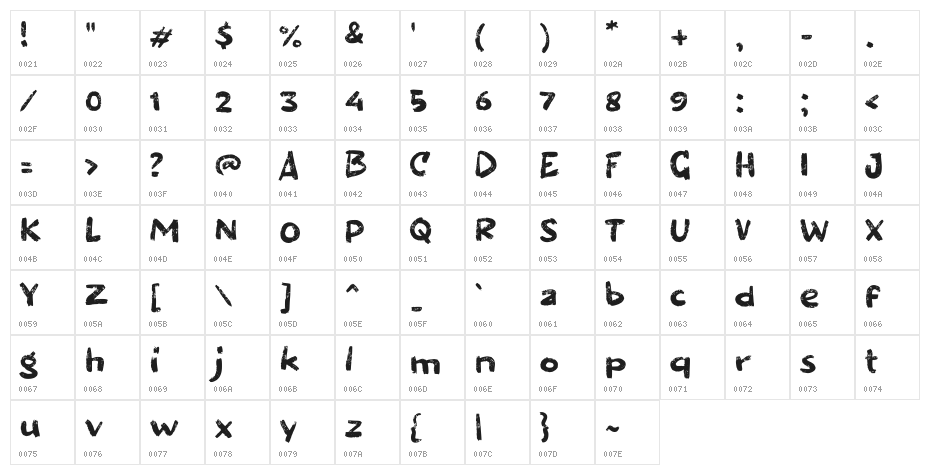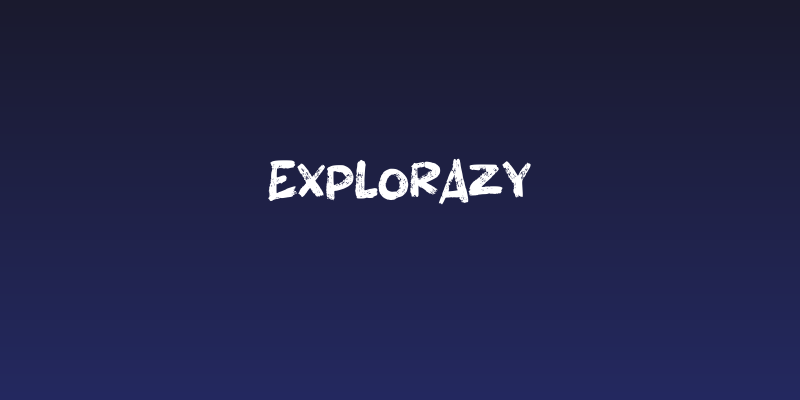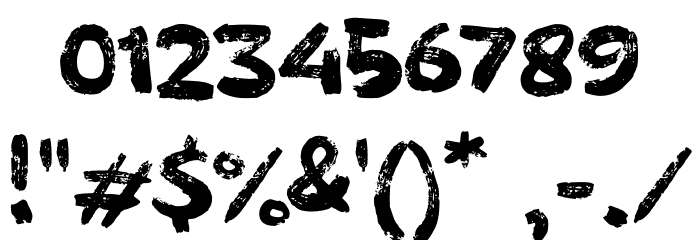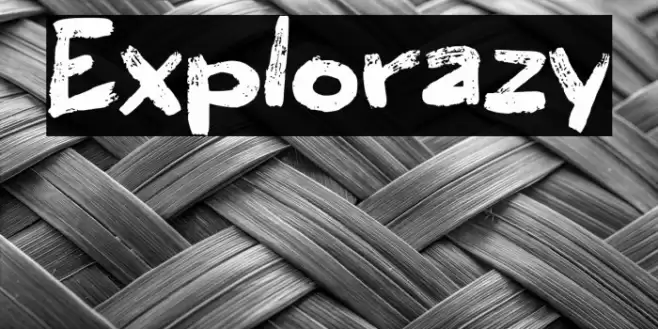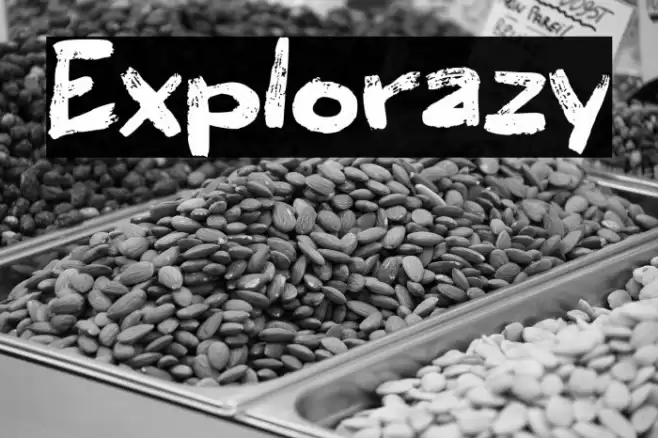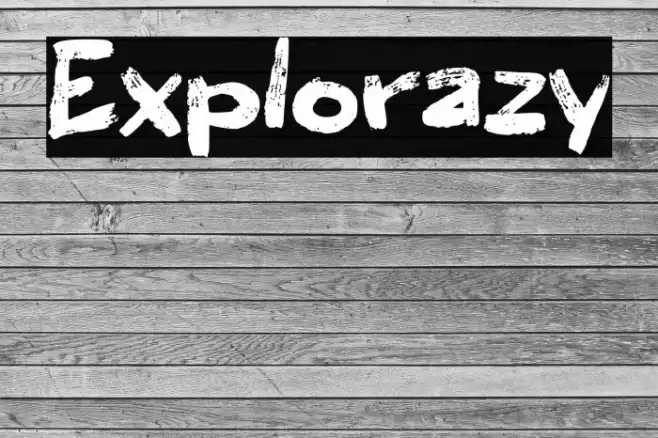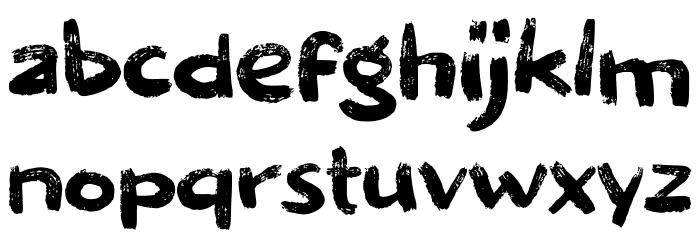
Explorazy Font
✎ Messy
| カテゴリ | Messy |
| 全体的なスタイル | Grunge, Urban, Artistic |
| おすすめプロジェクト | Ideal for posters, album covers, streetwear branding, and artistic projects that require a bold statement. |